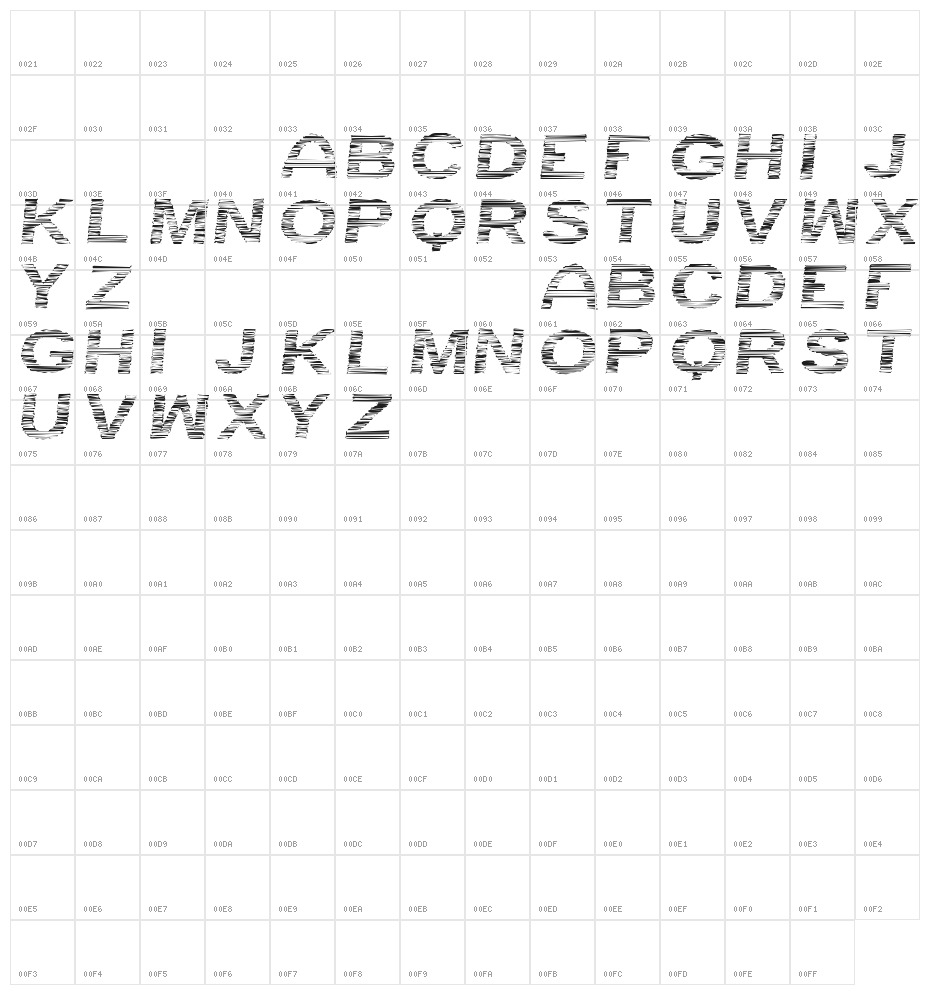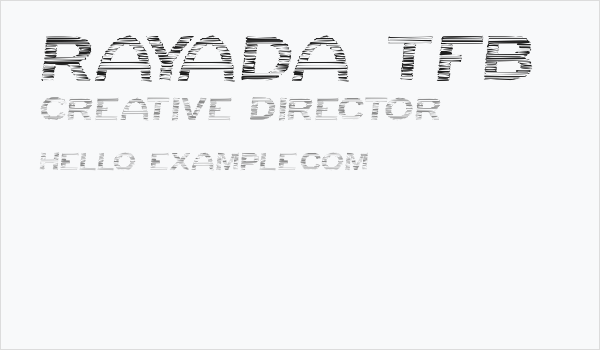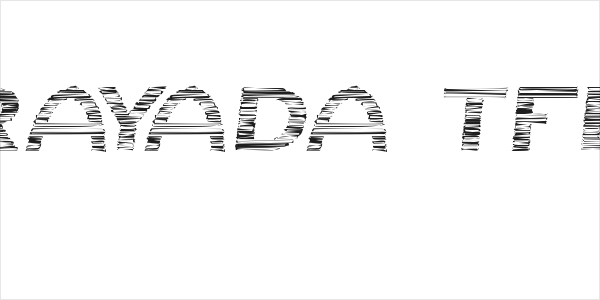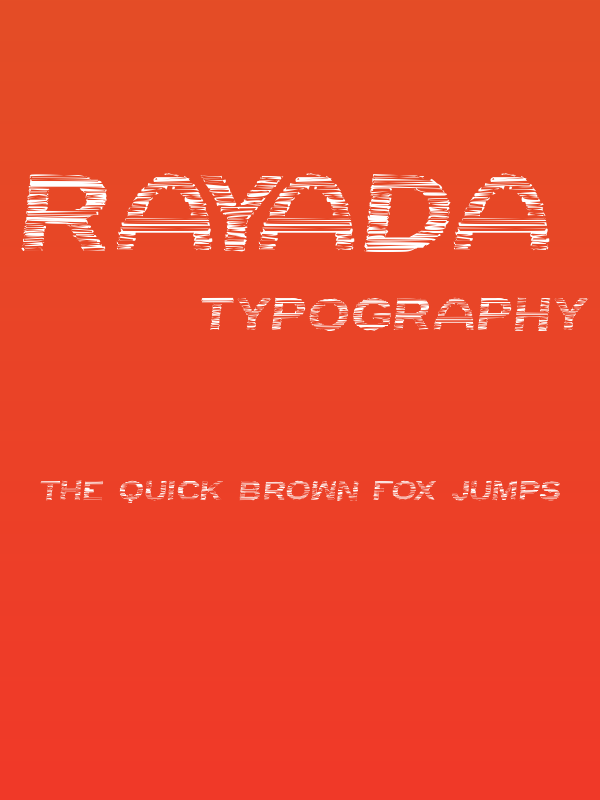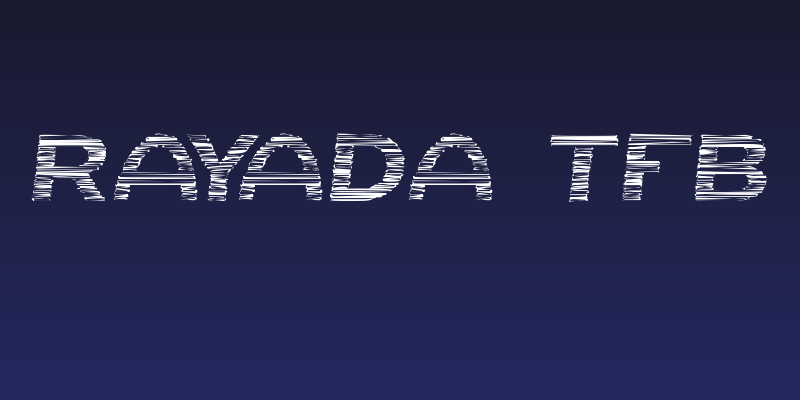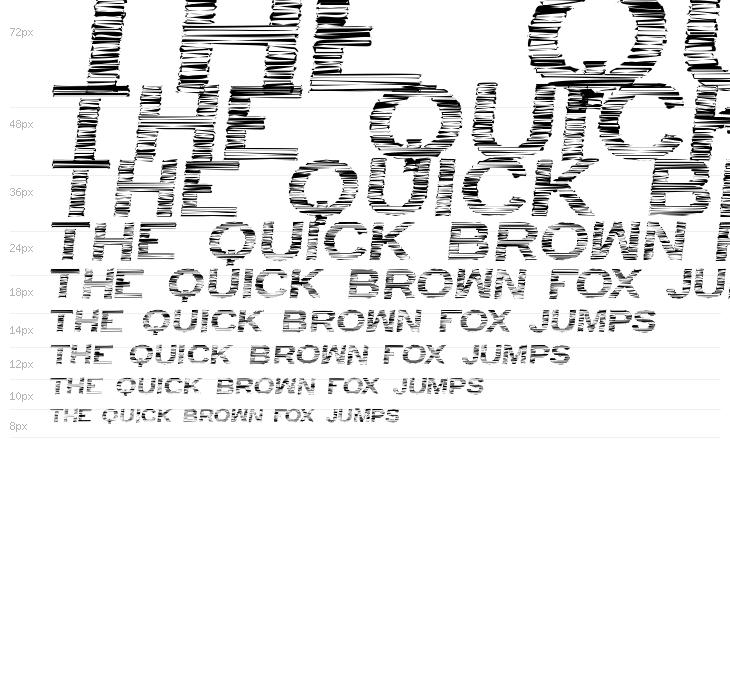
Rayada tfb Font
✎ Distorted Eroded
| Proyectos propuestos | Ideal for posters, album covers, branding materials, and any design needing a bold, artistic touch. |